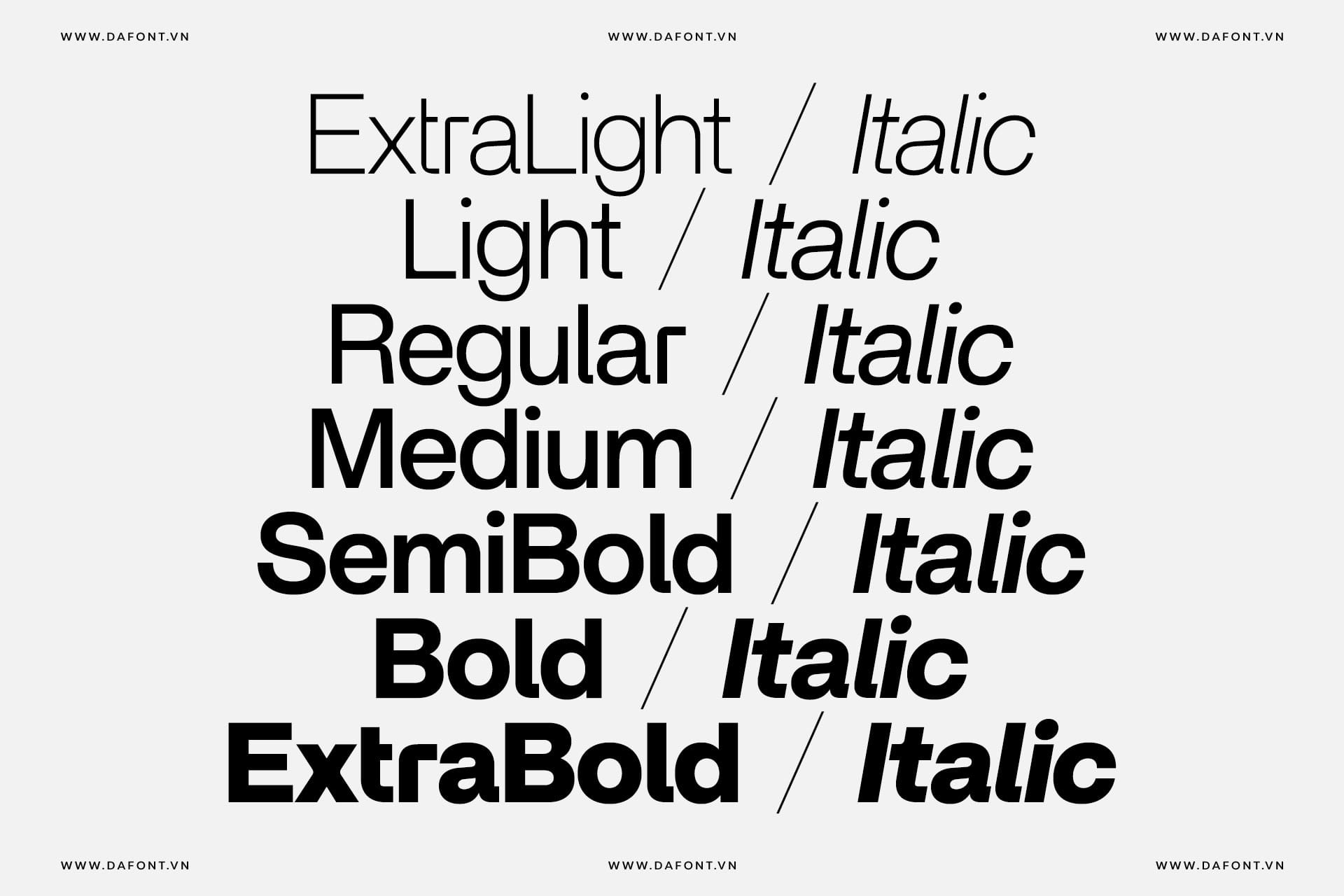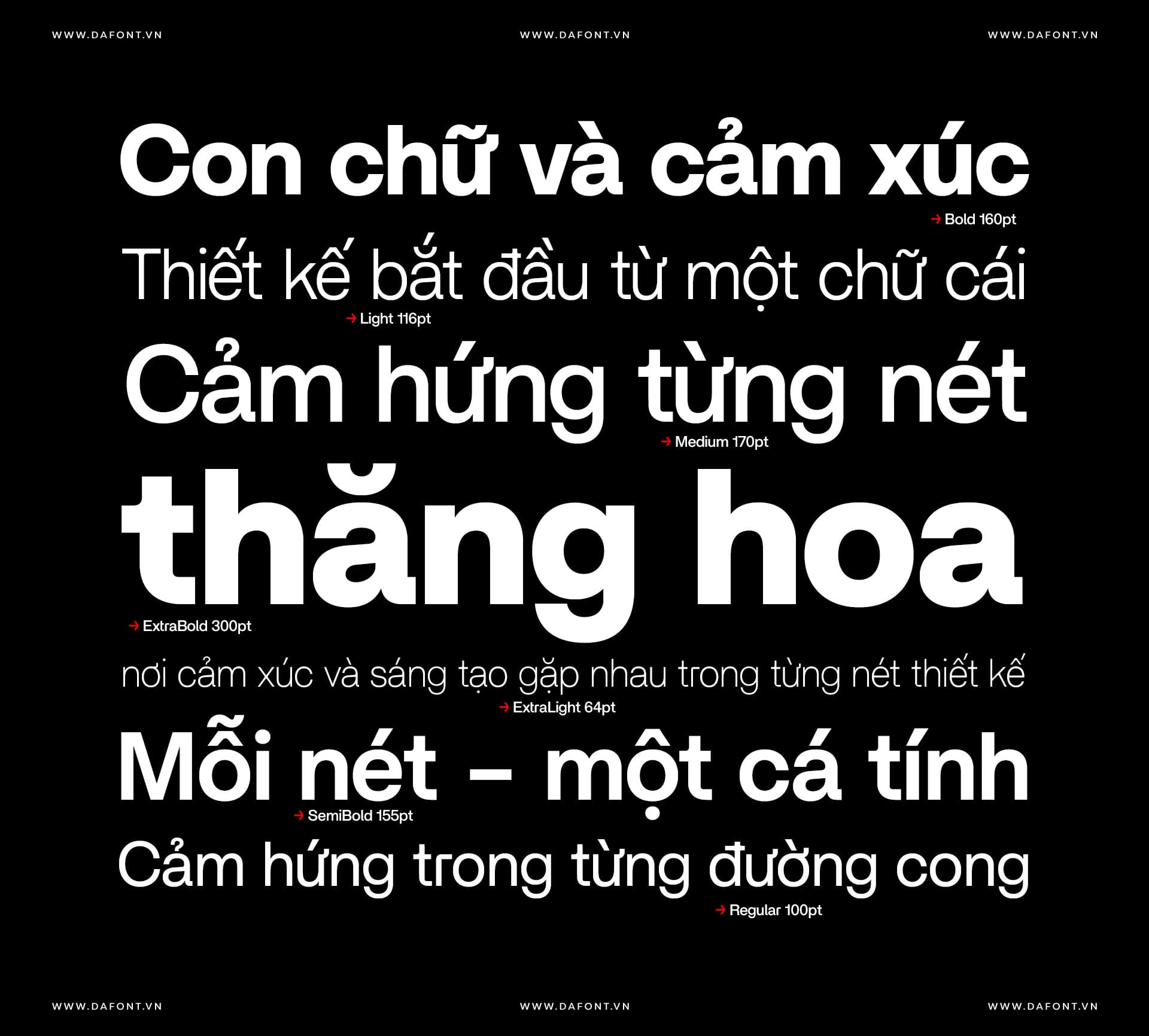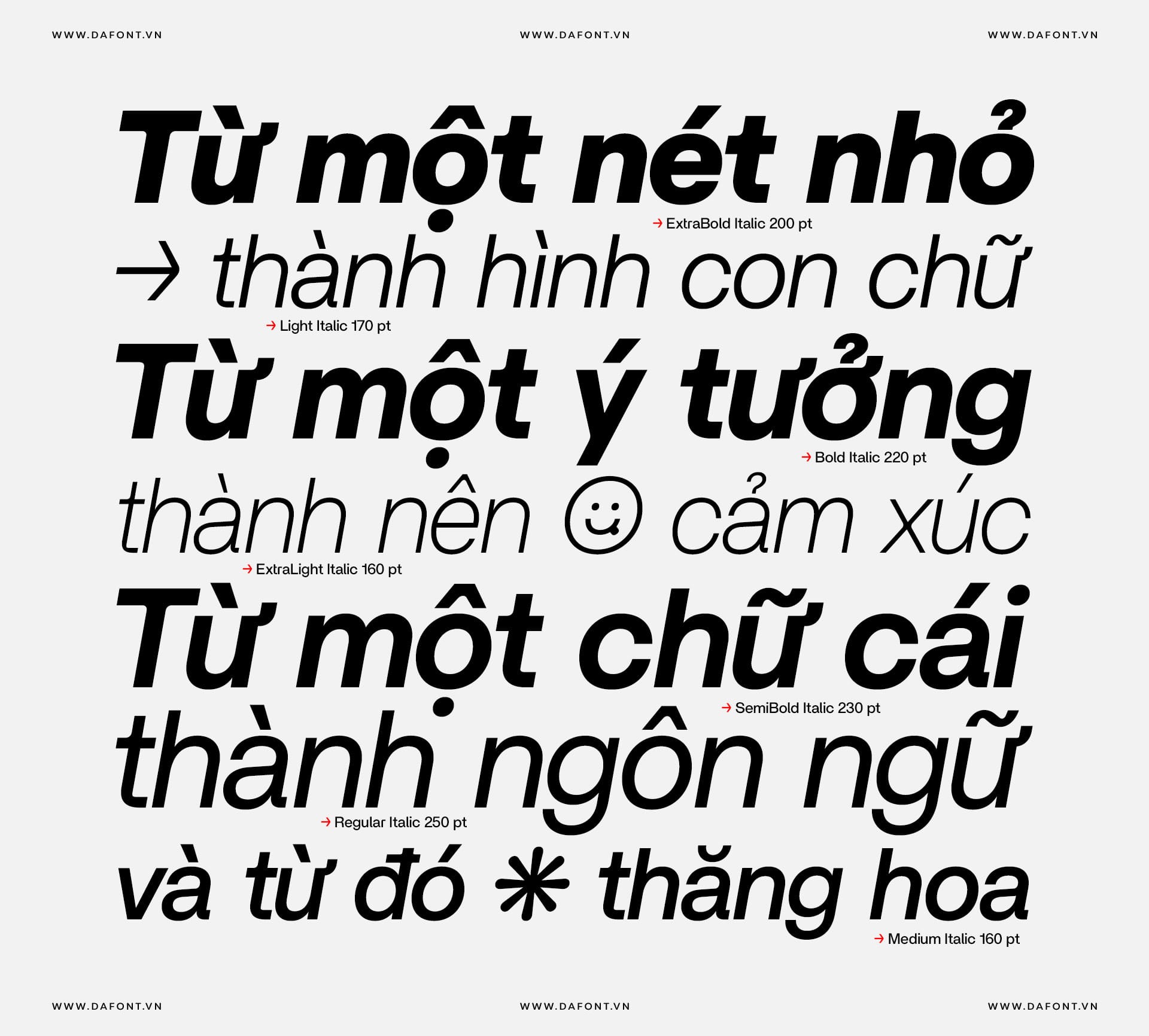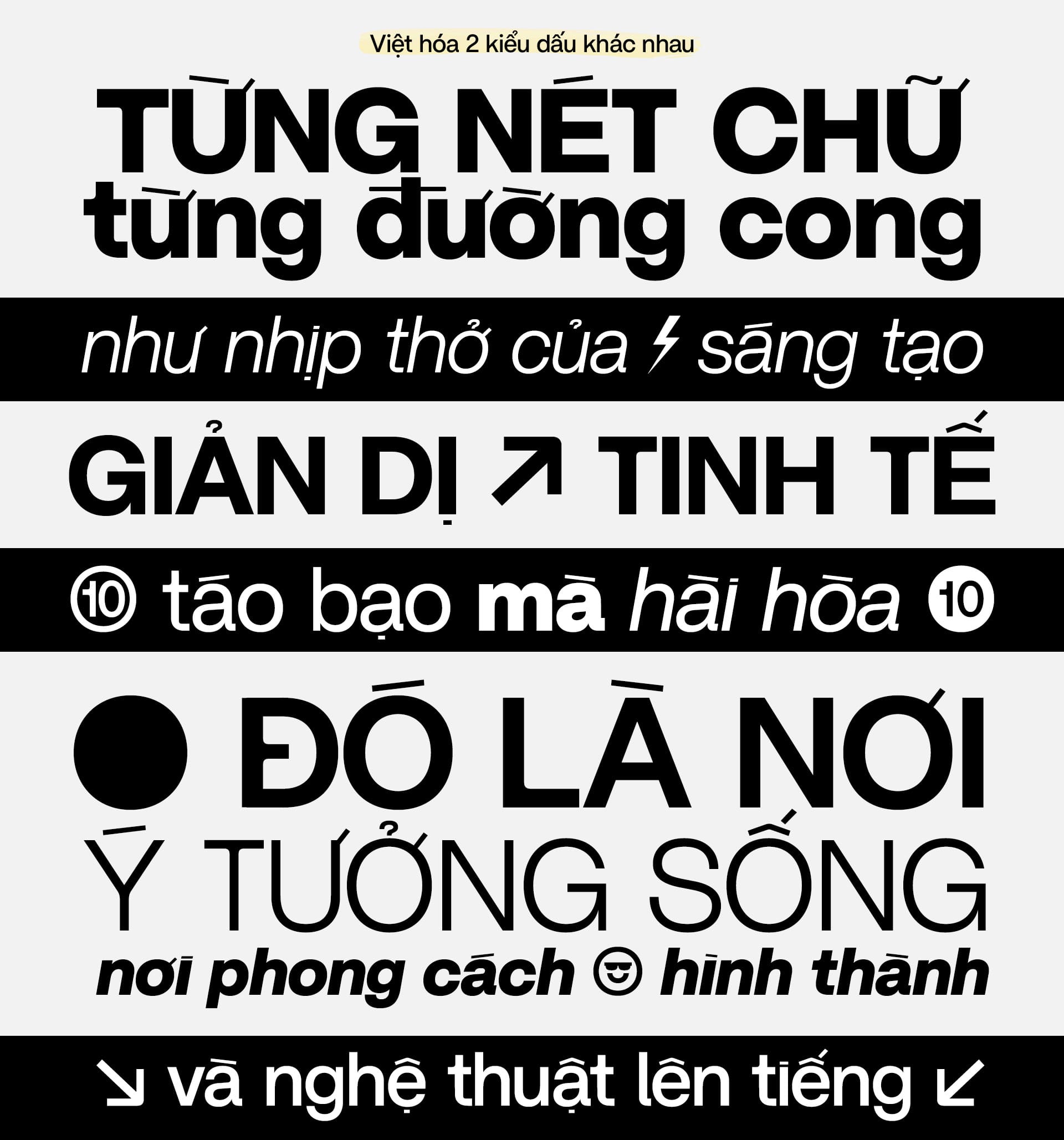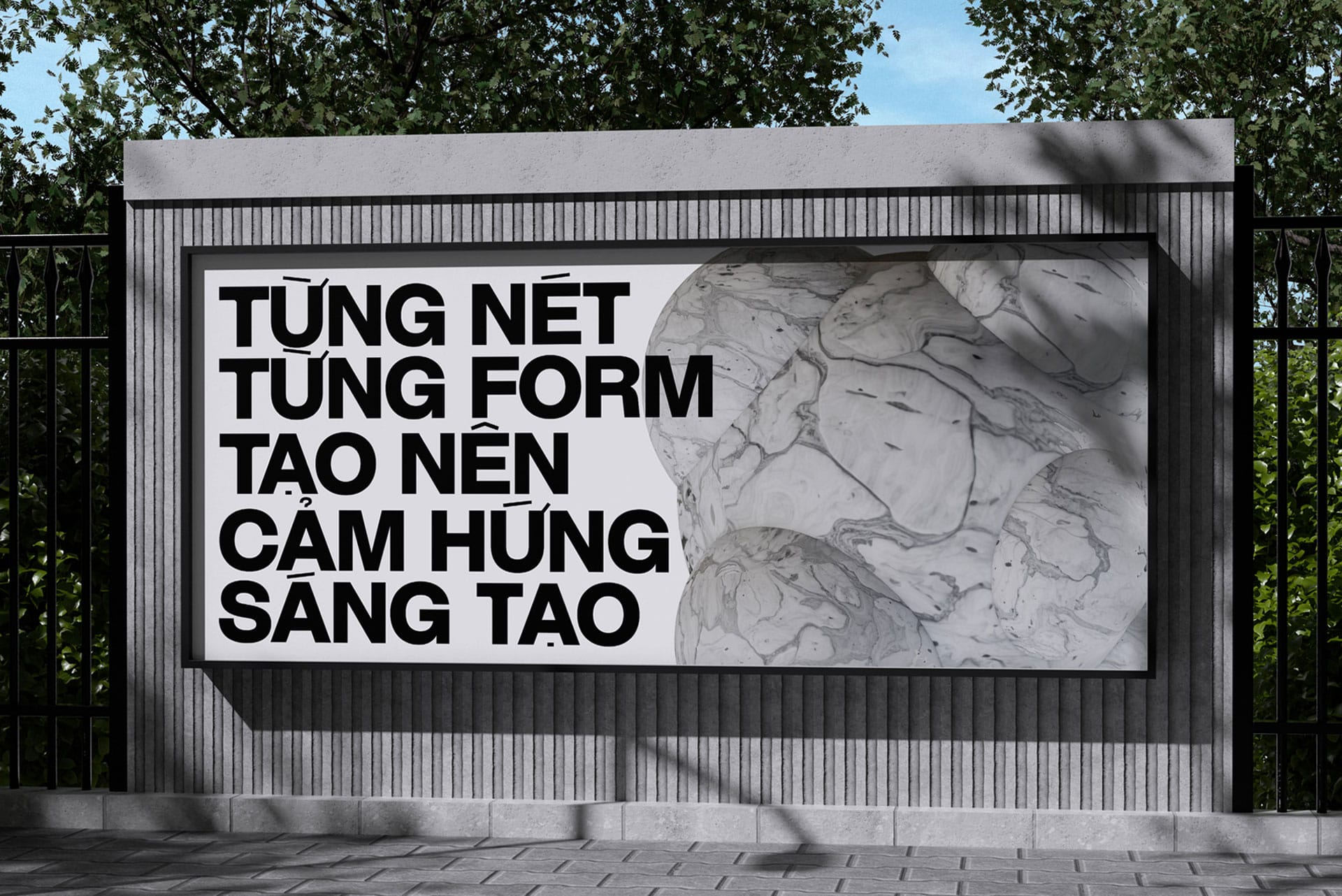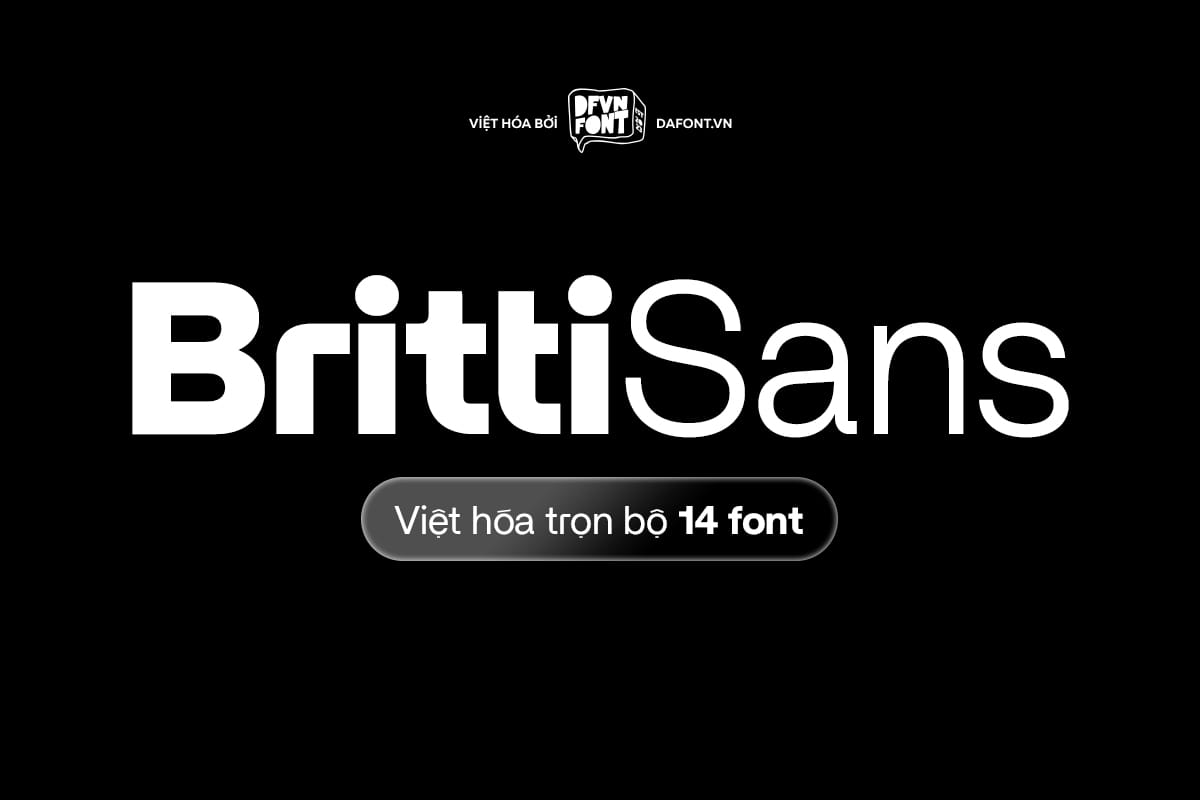
DFVN Britti Sans là một bộ chữ sans-serif kiểu neo-grotesque hiện đại với đường nét hình học tinh gọn, bao gồm 14 kiểu chữ phù hợp cả tiêu đề lẫn nội dung dài trong in ấn và giao diện số.
Britti Sans chịu ảnh hưởng nguyên tắc thiết kế công nghiệp và tinh thần Swiss mid‑century, tối ưu cho tính rõ ràng, cân đối, dễ đọc ở nhiều kích cỡ. Thiết kế giữ vẻ tối giản nhưng có nhấn mạnh các chi tiết hình học và độ tương phản thấp, tạo cảm giác đương đại và đa dụng.
Đặc điểm nổi bật của DFVN Britti Sans
Britti Sans font là bộ font chữ sans-serif mang đến cảm giác hiện đại, dễ đọc ở mọi kích thước – từ tiêu đề lớn đến văn bản nhỏ. Một số đặc điểm nổi bật của Britti Sans font bao gồm:
- Hỗ trợ đa ngôn ngữ: Bao quát các ký tự đặc biệt như Sharp S (ß) tùy chỉnh cho chữ hoa/thường, lý tưởng cho nội dung tiếng Việt hoặc châu Âu.
- Biểu tượng phong phú: Từ ký hiệu tiền tệ (kể cả Bitcoin ₿) đến emojis, icons, giúp font này phù hợp cho thiết kế web và app.
- Tính năng OpenType: Contextual alternates, số bảng (tabular numbers), phân số, và số vòng tròn – tất cả giúp tùy chỉnh linh hoạt mà không cần phần mềm phức tạp.
- Phiên bản linh hoạt: Bộ font bao gồm 7 weight kèm theo các phiên bản italic tương ứng, tổng cộng 14 phong cách (styles) — mang lại sự linh hoạt tối đa cho mọi nhu cầu thiết kế, từ tiêu đề nổi bật đến nội dung tinh gọn.
- Bộ font được Việt hóa với 2 kiểu dấu khác nhau: Một kiểu giữ nguyên phong cách dấu gốc và một kiểu dấu mảnh tinh tế, giúp người dùng linh hoạt lựa chọn tùy theo phong cách thiết kế. Nhờ đó, bạn có thể dễ dàng ứng dụng trong nhiều bối cảnh khác nhau — từ các thiết kế mang sắc thái cổ điển đến hiện đại, từ tiêu đề nổi bật đến nội dung thanh thoát, mà vẫn đảm bảo tính thẩm mỹ và nhất quán trong toàn bộ dự án.
Ứng dụng thực tế của Britti Sans trong thiết kế
DFVN Britti Sans khẳng định sức hút của mình trong mọi lĩnh vực nhờ khả năng ứng dụng linh hoạt. Trong thiết kế web, font mang lại giao diện sạch sẽ, hiện đại và tối ưu hiệu suất nhờ hỗ trợ định dạng WOFF2 cho tốc độ tải nhanh. Với nhận diện thương hiệu, Britti Sans thể hiện vẻ đẹp công nghiệp mạnh mẽ, lý tưởng cho các logo thời trang, công nghệ hay doanh nghiệp sáng tạo. Trong in ấn, các tính năng như tabular numbers giúp trình bày số liệu và báo cáo tài chính một cách chuyên nghiệp, cân đối.
Gợi ý sử dụng: Hãy thử kết hợp Britti Sans Bold cho tiêu đề trên website thương mại điện tử và Regular cho phần mô tả sản phẩm – bạn sẽ có một thiết kế vừa hiện đại, dễ đọc lại đậm chất chuyên nghiệp.
DFVN Britti Sans Việt hóa Preview
DFVN Britti Sans là lựa chọn rất mạnh cho các designer và thương hiệu muốn một font sans-serif hiện đại, sạch sẽ, linh hoạt và có cá tính hình học. Nếu bạn đang tìm một font để làm nổi bật tiêu đề, xây dựng thương hiệu, thiết kế UI/UX hoặc in ấn với phong cách hiện đại – Britti Sans xứng đáng được xem xét.
Bộ font DFVN Britti Sans được Việt hóa cẩn thận, tất cả các ký tự và dấu được tối ưu hóa lại cho phép hiển thị tốt hơn, kerning toàn bộ ký tự.